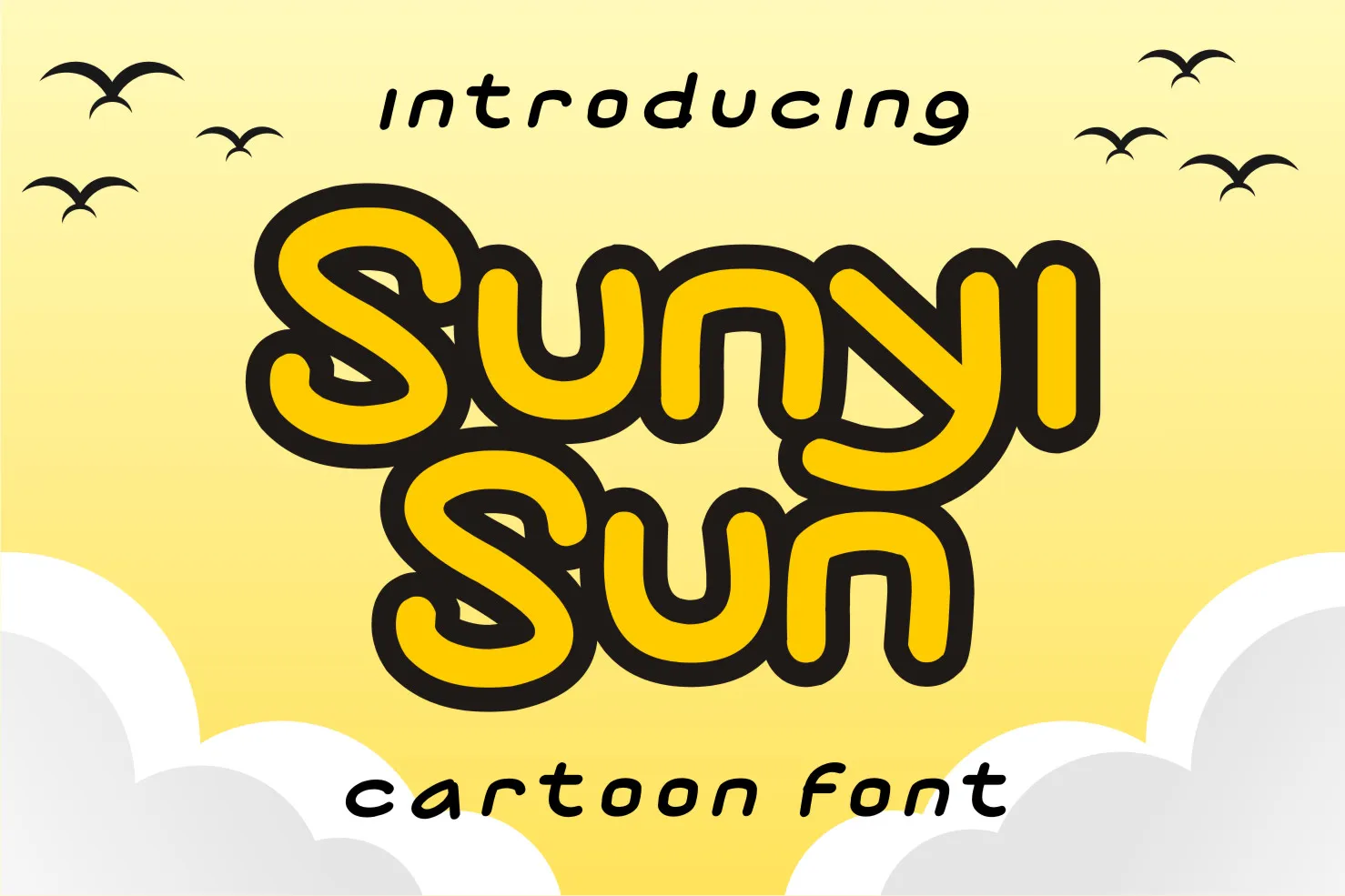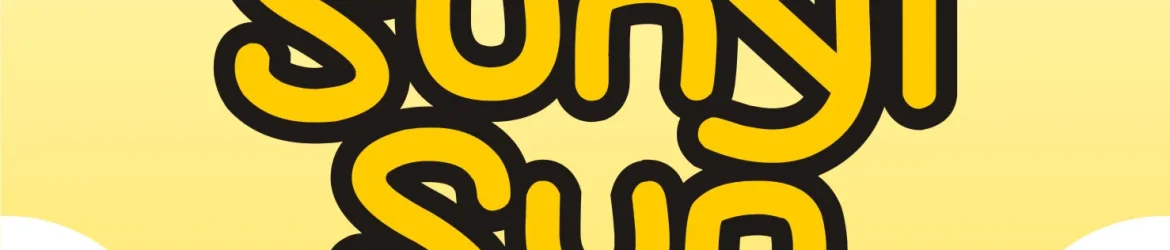
Sunyi Sun Font – Download Grátis
Aqui está uma descrição para a página de download da font ‘Sunyi Sun Font’, focada em suas características naturais e envolventes: Com seu estilo informal e sua vibe casual, o ‘Sunyi Sun Font’ é um belo recurso gráfico que se destaca no mercado dos tipos de exibição. Suas linhas leves e simples criam uma aparência moderna que se encaixa perfeitamente em qualquer layout digital ou impressão. Esta fonte carece de qualquer excessos formais, oferecendo um toque natural que ajuda a criar ambientes descontraídos e relaxantes. Sem dúvidas, é ideal para projetos que exigem uma aparente simplicidade e um ar casual, permitindo que designers e criativos façam o máximo do seu potencial em qualquer mídia. Com o ‘Sunyi Sun Font’, você pode adicionar um toque de frescura a qualquer projeto digital ou impresso, reforçando a personalidade e o estilo que cada trabalho merece.